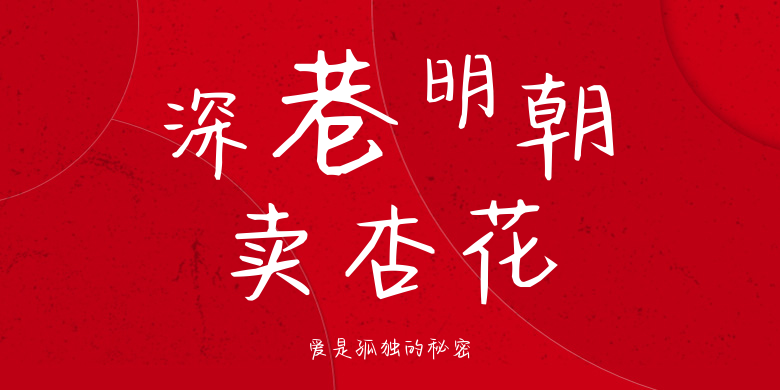
爱是孤独的秘密
爱是孤独的秘密,这款字体结构工整、笔画清晰,兼顾美观与易读性,适用于标题、正文、海报、包装、LOGO 等多种场景。字形优雅稳定,风格百搭耐看,适配日常排版与创意设计,让文字呈现更舒适、更具质感。爱是孤独的秘密一笔一画,皆是细节,以均衡的比例、流畅的线条打造舒适视觉体验,字形端正大气,风格简约现代。无论是商业设计、品牌宣传还是日常排版,都能轻松驾驭,让文字更有格调与力量。爱是孤独的秘密字体下载。